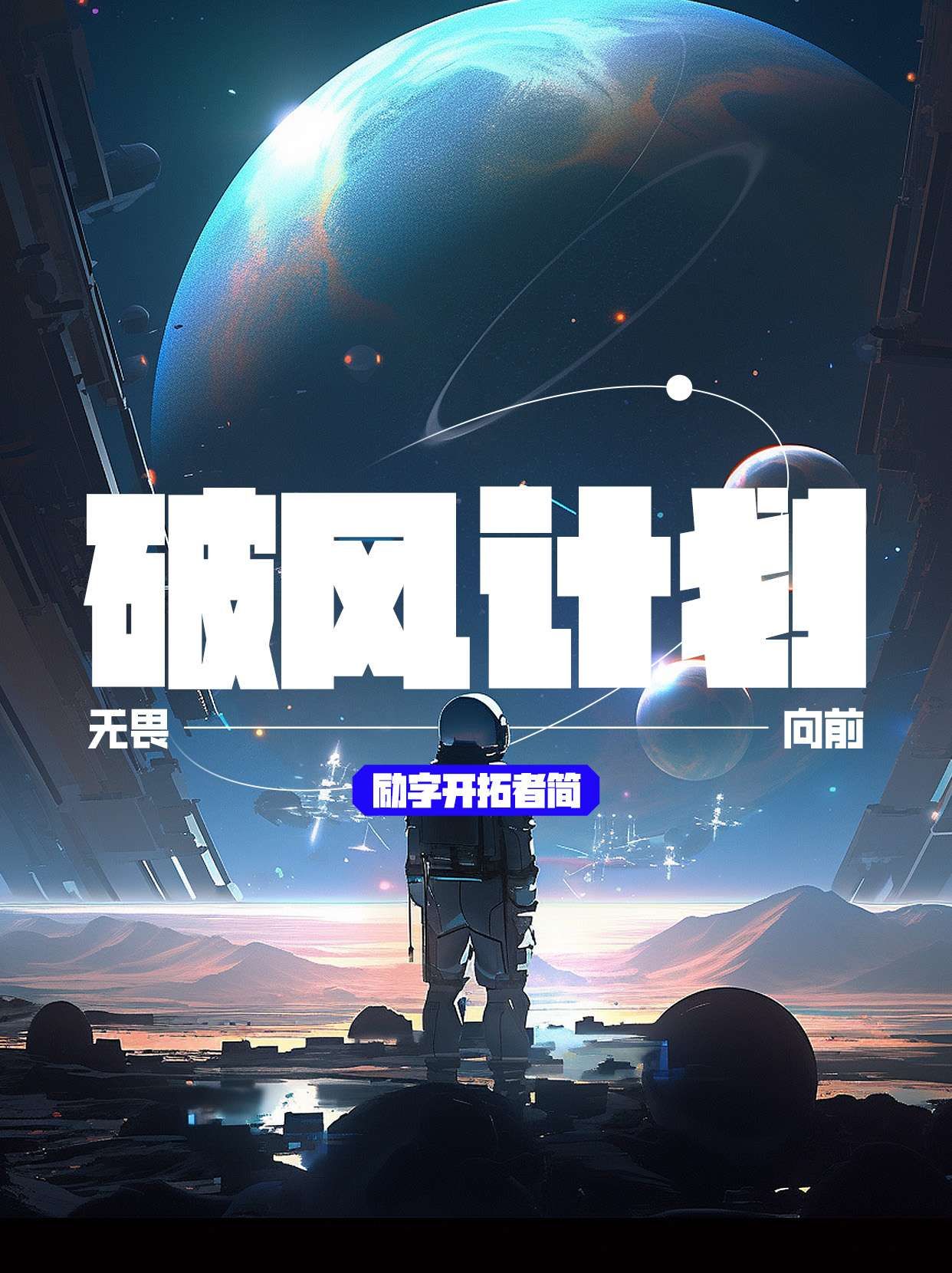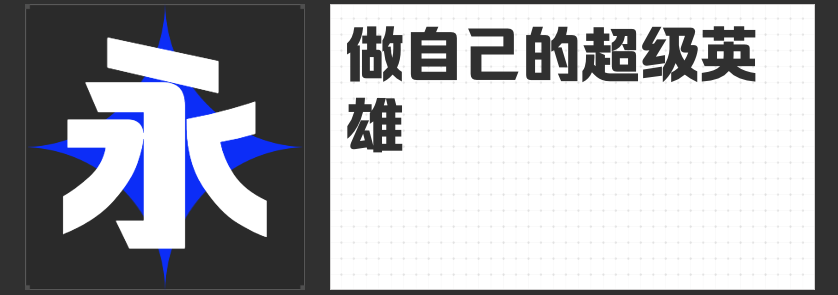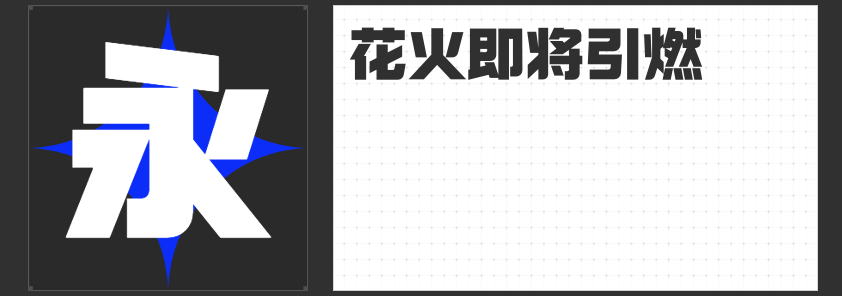
强视觉冲击力!推荐四款“励字”系列超粗字重字体
在字体设计领域,粗字重的字体往往能够带来强烈的视觉冲击力,让人一眼难忘。今天来为大家推荐四款来自“励字”系列的超粗字重字体。
首先,我们来看看“励字勇敢黑简 超黑”。这款字体以其粗犷而不失优雅的线条,展现出了独特的视觉魅力。无论是用于标题设计还是海报制作,都能够迅速吸引人们的目光,让作品在众多信息中脱颖而出。
接下来是“励字开拓者简 超级黑”。与“超黑”相比,这款字体在字重上更进一步,呈现出更加厚重、稳重的视觉效果。它非常适合用于正式场合的文档排版或品牌标识设计,能够彰显出品牌的权威性和专业度。
再来看看“励字超级勇士简 超粗”。这款字体以其极粗的线条和独特的字形设计,展现出了强烈的个性和力量感。它非常适合用于需要强烈视觉冲击力的场合,如电影海报、游戏宣传图等,能够瞬间点燃观众的热情。
最后是“励字跨界黑简 超级黑”。这款字体在保持粗犷风格的同时,还融入了现代简约元素,使其既具有传统字体的韵味,又不失现代感。它非常适合用于各种创意设计和广告宣传中,能够轻松驾驭各种风格,为作品增添独特的魅力。
总的来说,这四款“励字”系列的超粗字重字体都以其独特的视觉效果和强烈的冲击力,成为了设计师们的心头好。它们不仅适用于各种创意设计和广告宣传,还能够为作品增添独特的个性和品味。如果你正在寻找一款能够让你的作品在众多信息中脱颖而出的字体,那么不妨试试这四款“励字”系列的超粗字重字体吧!